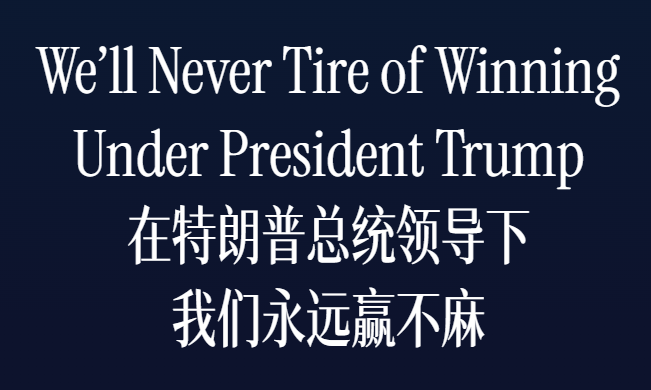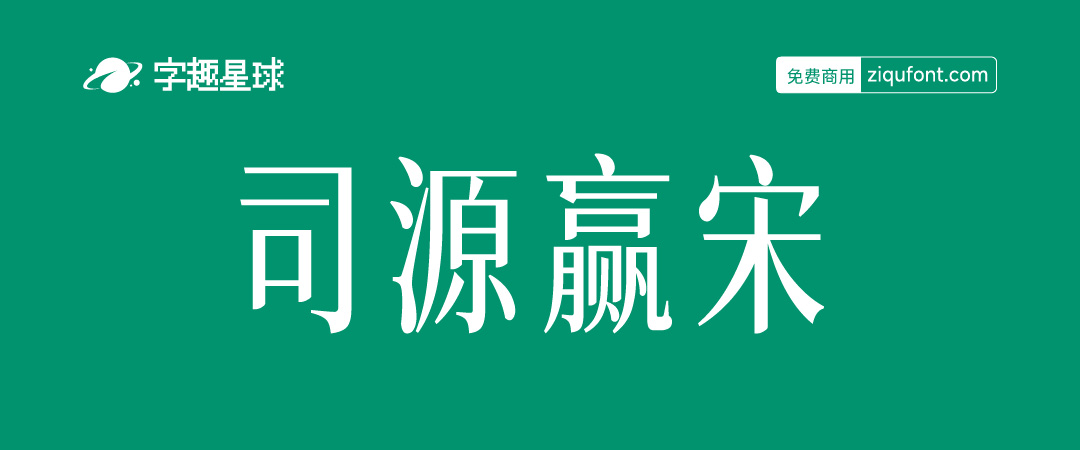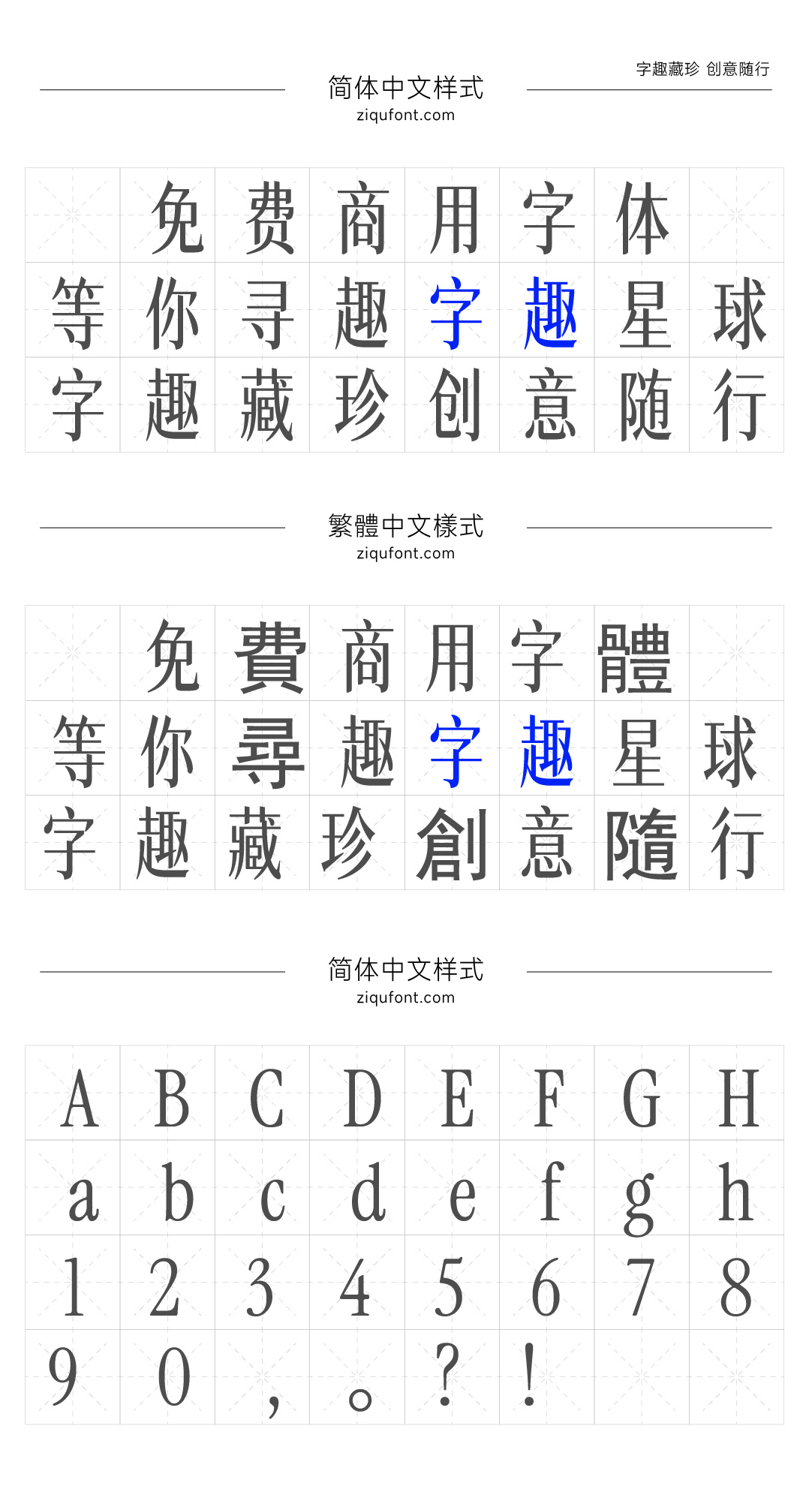
清明回家突然想到,怎么没人给白宫官网这个标题字体搭配中文的。
右键检查了下,是个 OFL 授权的开源字体 Instrument Serif,1个字重及对应斜体(上图的“The”便是)
网上也有人做了模仿白宫官网的网页,但字体不到位,原因是,虽然 CSS 可以强行挤窄文字,但中英混排不佳。
与其纠结代码,何不预制一个现成的中英混排白宫字体?
司源赢宋
一晚上做出来了,就叫“司源赢宋”,若软件不能显示中文名,其后备名称为“CorpSrcWinSong”。
显然汉字部分又是思源改。由于Source Han Serif © Adobe, with Reserved Font Name ‘Source’.
所以思源改不让用“思源\Source”为名,因此字体名用“Src”,“源”。
既然名为“宋”,当然只能是宋体,凡是非宋体字形一概删除⸺思源宋的假名、注音、谚文就都删了。
虽说有宋体谚文,但不是 OFL 的(如有请告知!)